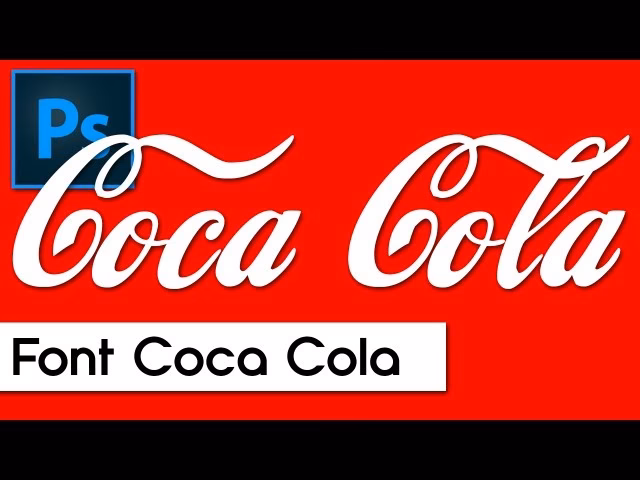
Når du ser Coca-Colas logo, er der ingen tvivl. Den flydende, elegante skrift er øjeblikkeligt genkendelig over hele verden og er blevet synonym med brandet selv. Men hvad er historien bag denne karakteristiske skrifttype, og hvad gør den så unik og holdbar?
Coca-Colas logo er ikke baseret på en standard skrifttype, du kan købe og installere på din computer. Det er et specialdesignet logo, der dog trækker dybe rødder i en specifik skriftstil, der var populær i USA i slutningen af det 19. århundrede: Spencerian Script.
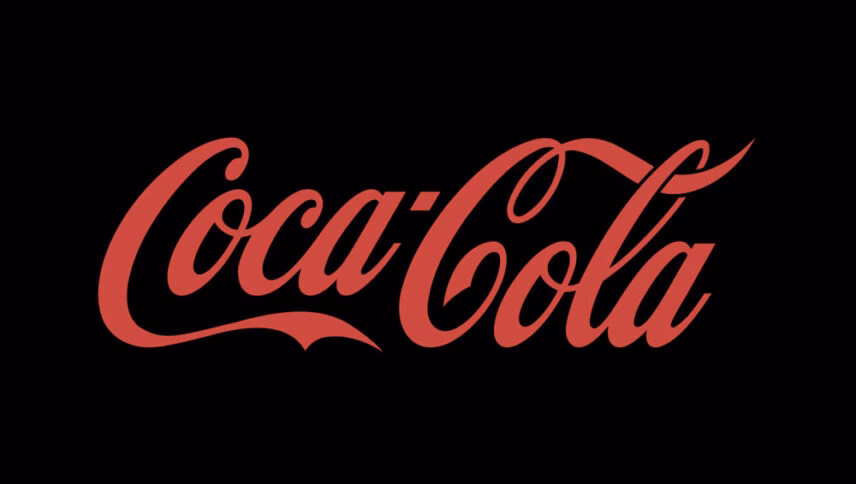
Hvad er Spencerian Script?
Spencerian Script er en form for kalligrafisk håndskrift, der blev udviklet af Platt Rogers Spencer i midten af 1800-tallet i USA. Den blev hurtigt standarden for forretningskorrespondance og blev udbredt undervist i handelsskoler og senere i de offentlige skoler. Stilen er kendt for sine flydende, sammenhængende bogstaver, variation i strøgbredden (tykke nedstreger og tynde opstreger), og ofte elegante udsmykninger, især på store bogstaver. Den har typisk en lille x-højde (højden på små bogstaver uden op- eller nedstreger) og karakteristisk lange, svingende op- og nedstreger.
Denne skriftstil var et udtryk for en tid, hvor personlig håndskrift var den primære form for kommunikation, især i forretningsverdenen. Den lagde vægt på både læsbarhed og en vis grad af kunstnerisk flair, hvilket gjorde dokumenter og korrespondance både funktionelle og æstetisk tiltalende.
Coca-Colas Forbindelse til Spencerian Script
Da Coca-Cola blev grundlagt af Dr. John Stith Pemberton i 1886, blev logoet håndskrevet af hans bogholder, Frank M. Robinson. Robinson var en mester i Spencerian Script, og det var denne stil, han brugte til at skrive navnet "Coca-Cola". Logoet blev første gang registreret som varemærke den 31. januar 1893.
Det bemærkelsesværdige er, hvor konsekvent Coca-Colas logo er forblevet gennem over 130 år. Selvom der har været mindre justeringer og moderniseringer – for eksempel er skriften i dag lidt federe og mere afrundet visse steder sammenlignet med den oprindelige håndskrift – er kernen i Spencerian Script-stilen intakt. Denne konsistens har bidraget enormt til brandets genkendelighed og tidløse appel.
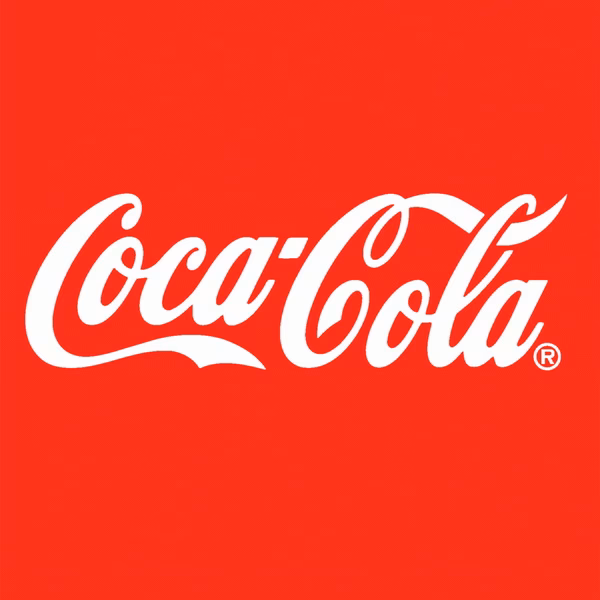
Brugen af Spencerian Script gav logoet et personligt, håndlavet præg, selv da produktionen blev masseindustri. Det signalerede elegance, tradition og en vis kvalitet, der var i tråd med datidens æstetik og forventninger til forretningspræsentation.
Spencerian-inspirerede Skrifttyper i Dag
Fordi Coca-Colas logo er et unikt design baseret på en historisk skriftstil, findes den eksakte "Coca-Cola skrifttype" ikke som en kommercielt tilgængelig skrifttype til almindelig brug. Dog findes der mange moderne digitale skrifttyper, der er inspireret af eller direkte baseret på Spencerian Script.
Disse digitale versioner af Spencerian Script varierer meget i stil og detaljer. Nogle er meget tæt på den oprindelige penmanship med elaborate udsmykninger og stor variation i strøgbredde, mens andre er mere strømlinede og ensartede for bedre læsbarhed i visse sammenhænge.
Eksempler på Spencerian-inspirerede Kommercielle Skrifttyper:
- Spencerian Palmer Penmanship Regular (Intellecta Design): En OpenType-skrifttype med meget elaborate store bogstaver og mange alternative tegn.
- Spencerian By Product Regular (Intellecta Design): Lidt mindre udsmykket end Palmer Penmanship, med mindre variation i strøgbredden, hvilket giver et mere ensartet udseende.
- Alexandra Script Normal (BA Graphics): Ligner skrifttyper som Exmouth, men med lidt mere fantasifulde store bogstaver.
- Kuenstler Script: Minder meget om den gratis skrifttype Palace Script, men med lidt mere afstand mellem bogstaverne.
- Edwardian Script: En klassisk Spencerian-stil med lidt mere udsmykkede store bogstaver.
Derudover findes en række andre skrifttyper, der er beslægtet med Spencerian eller viser dens indflydelse, såsom Balmoral, Citadel Script, Elegy, English Script, Gravura, Shelley Script og Snell Roundhand.
Anvendelse af Spencerian-inspirerede Skrifttyper
Spencerian-inspirerede skrifttyper er fremragende til at skabe et formelt, elegant eller nostalgisk udtryk. De egner sig bedst til:
- Overskrifter og titler
- Bryllupsinvitationer og lykønskningskort
- Certifikater og diplomer
- Initialer (store, udsmykkede startbogstaver i et afsnit)
- Logoer og branding, der ønsker at formidle tradition eller håndværk
Det er vigtigt at bemærke, at på grund af deres udsmykkede natur og variation i strøgbredden er Spencerian-inspirerede skrifttyper generelt ikke egnede til længere tekstblokke i små størrelser. De kan være svære at læse, når de bruges som brødtekst. De fungerer bedst, når de får plads til at folde sig ud og ofte i kombination med en mere simpel, letlæselig skrifttype (f.eks. en sans-serif) til resten af teksten i et design. For at undgå et rodet udtryk anbefales det også kun at bruge én skriftlig skrifttype i et design.
Coca-Colas logo er et fremragende eksempel på, hvordan en historisk skriftstil kan blive en tidløs og definerende del af et globalt brands identitet. Selvom den specifikke logo-skrift er unik og beskyttet, lever arven fra Spencerian Script videre i mange smukke digitale skrifttyper, der giver designere mulighed for at indfange en lignende følelse af elegance og historie.